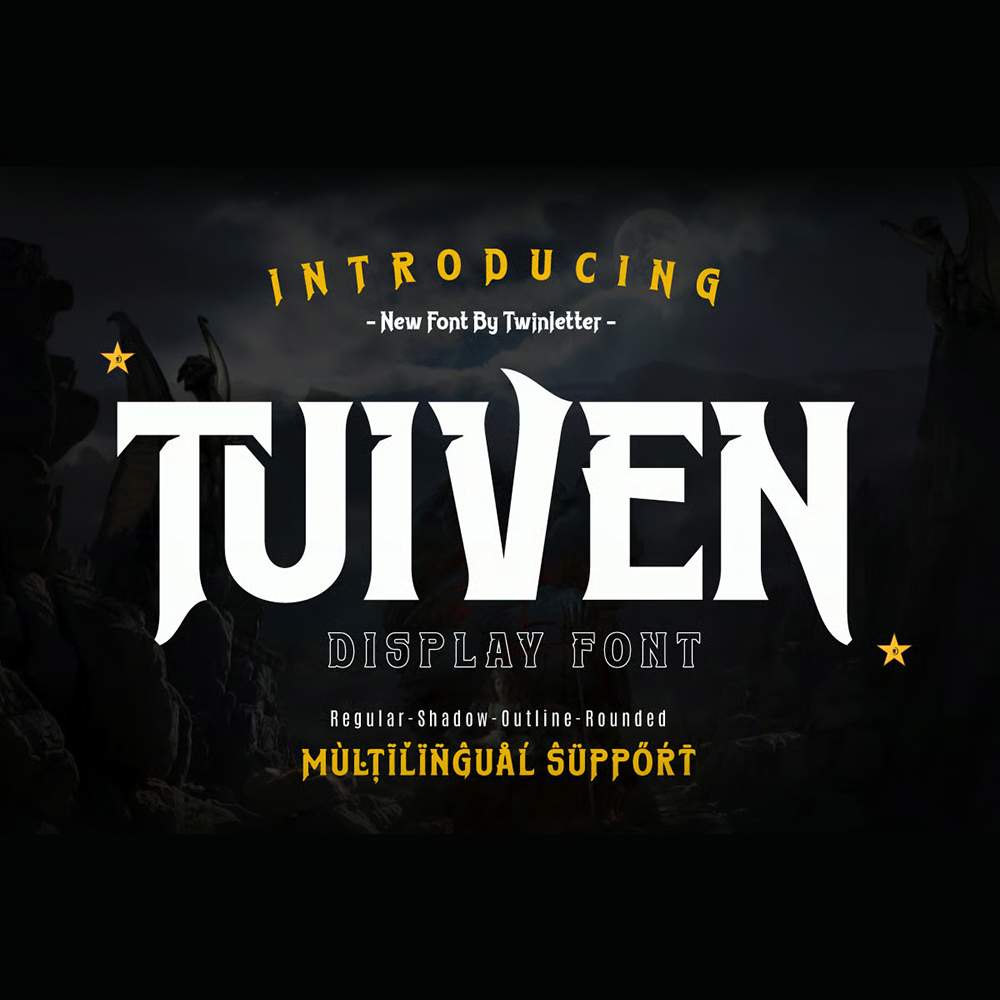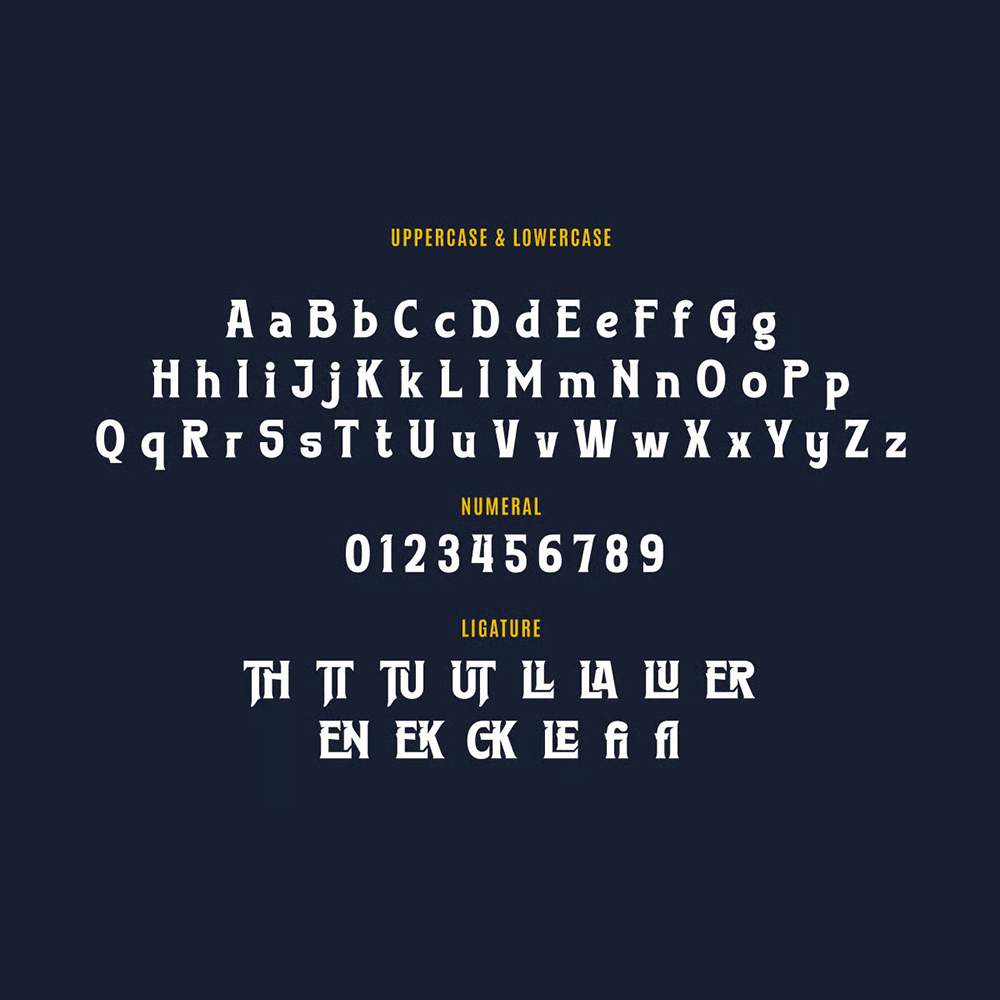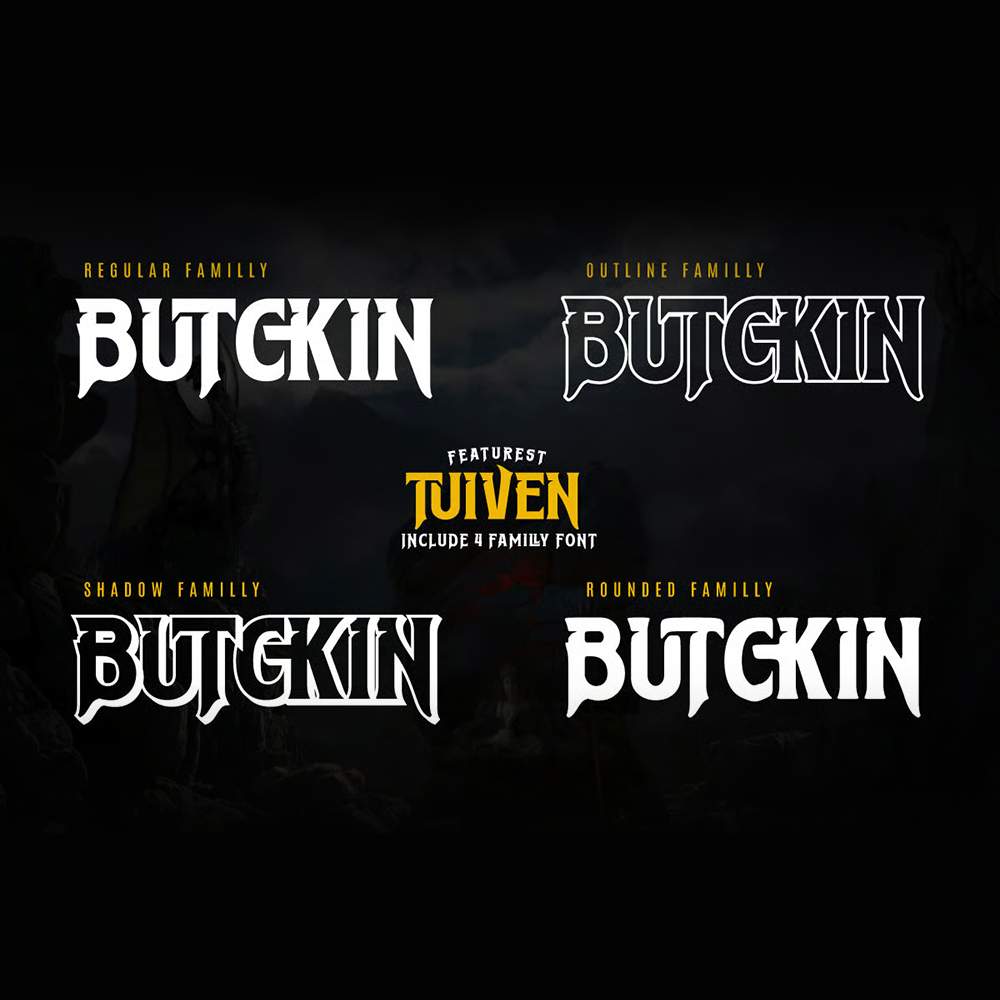
خانواده فونت پرمیوم و انگلیسی Tuiven Font یک فونت خاص برای افزودن حس تئاتری و سینمایی به پروژههای طراحی مرتبط با دنیای فیلم ایجاد شده است.…
خانواده فونت پرمیوم و انگلیسی Tuiven Font یک فونت خاص برای افزودن حس تئاتری و سینمایی به پروژههای طراحی مرتبط با دنیای فیلم ایجاد شده است. این فونت ظرافت و جسارت را با هم ترکیب میکند و ظاهری حماسی و خاطرهانگیز ایجاد میکند. حروف Tuiven دارای طراحی قوی و هنری با جزئیات دقیق و خطوط تمیز هستند. هر حرف حس جسارت و ظرافت را القا میکند و به متن جلوهای لوکس میبخشد. این فونت برای بهبود و دادن هویتی منحصر به فرد به عنوان فیلم، پوستر یا هر عنصر طراحی دیگر طراحی شده است. این فونت با ظاهری باشکوه و پر از شخصیت، هالهای از جدیت و حرفهای بودن را به نمایش میگذارد و آن را به انتخابی ایدهآل برای جلب توجه مخاطب در یک زمینه سینمایی تبدیل میکند.
مزایای استفاده از فونت لاتین Tuiven چیست؟